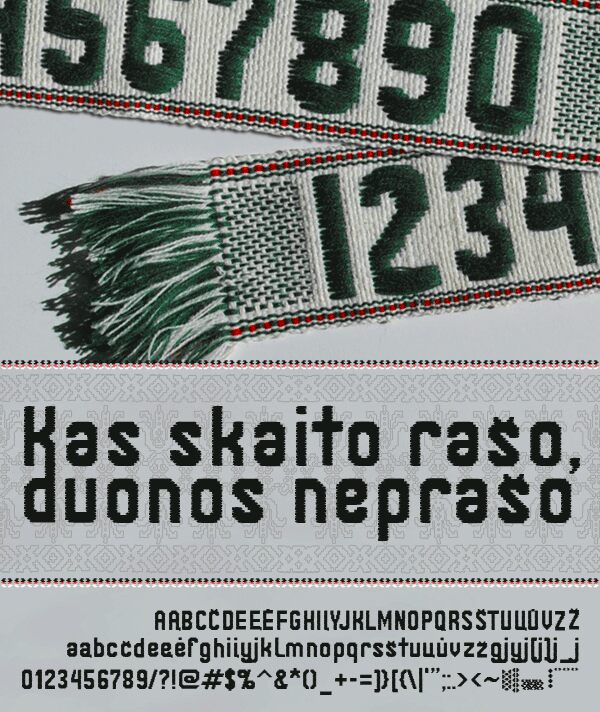
Janinos juosta
šriftas, nulipęs nuo tautinės juostos, savyje talpina lietuvišką abėcėlę, keletą ligatūrų ir dekoratyvinių raštų. jei turi ką apie tai pasakyti: labas@mono.lt